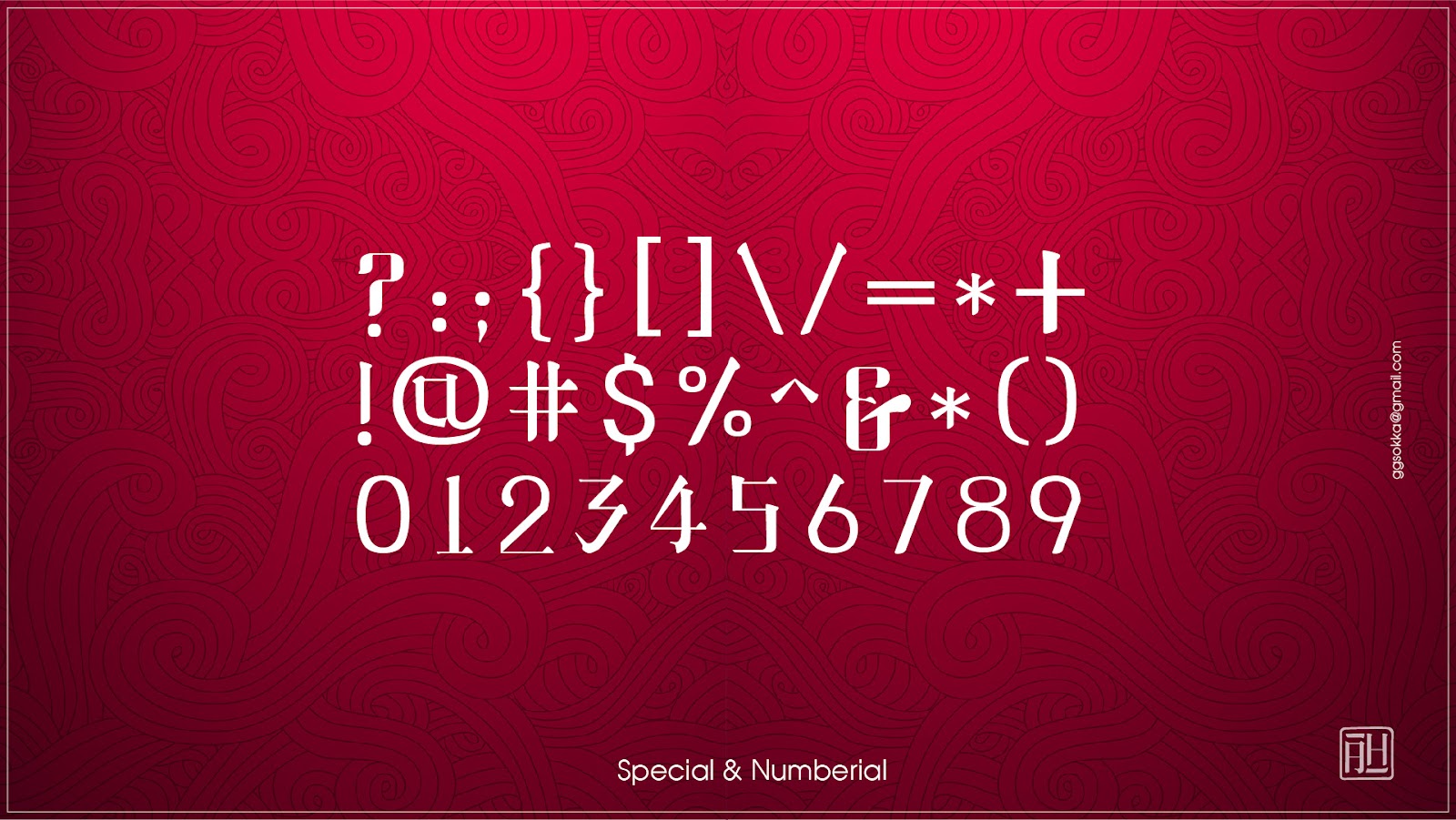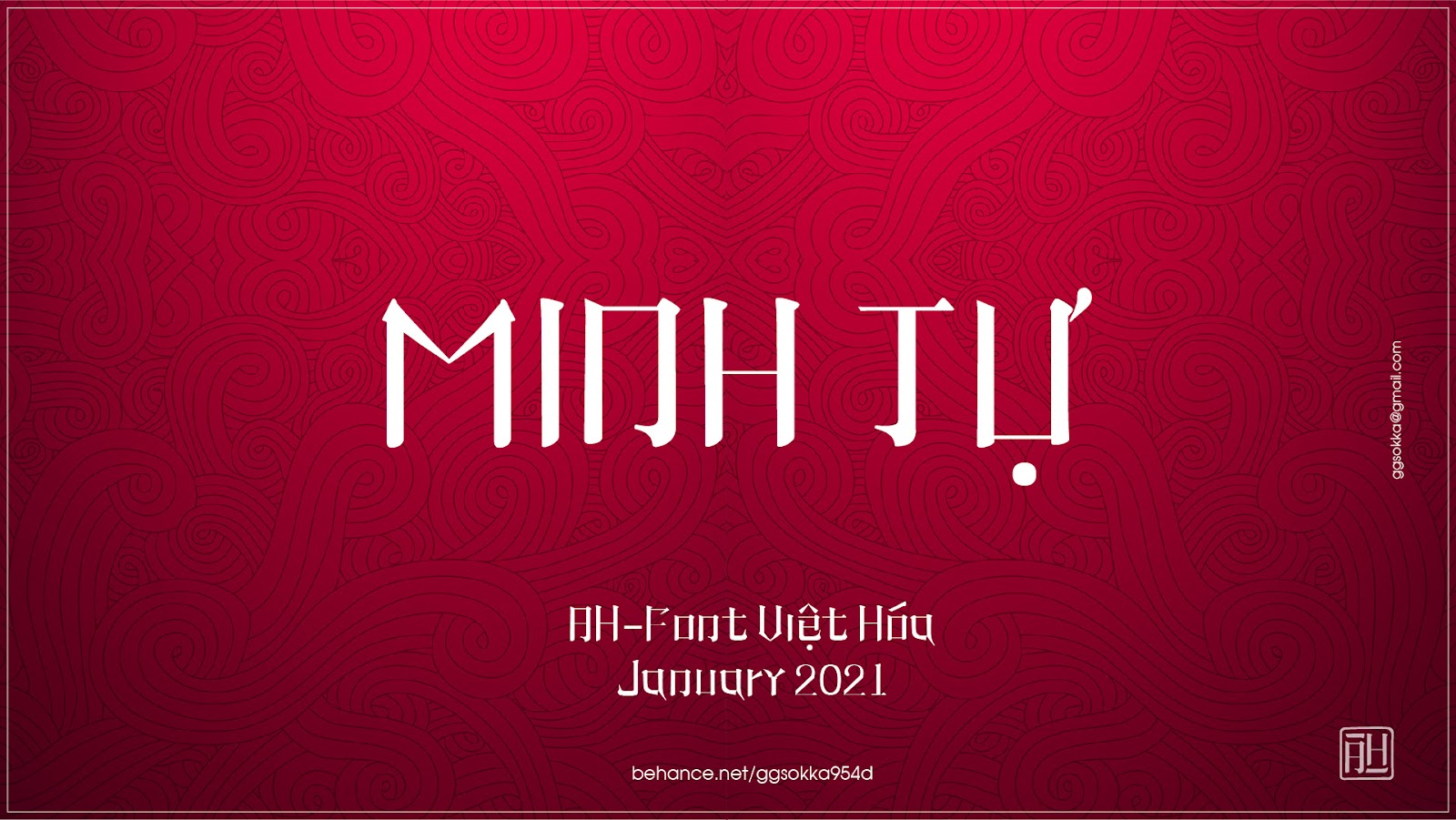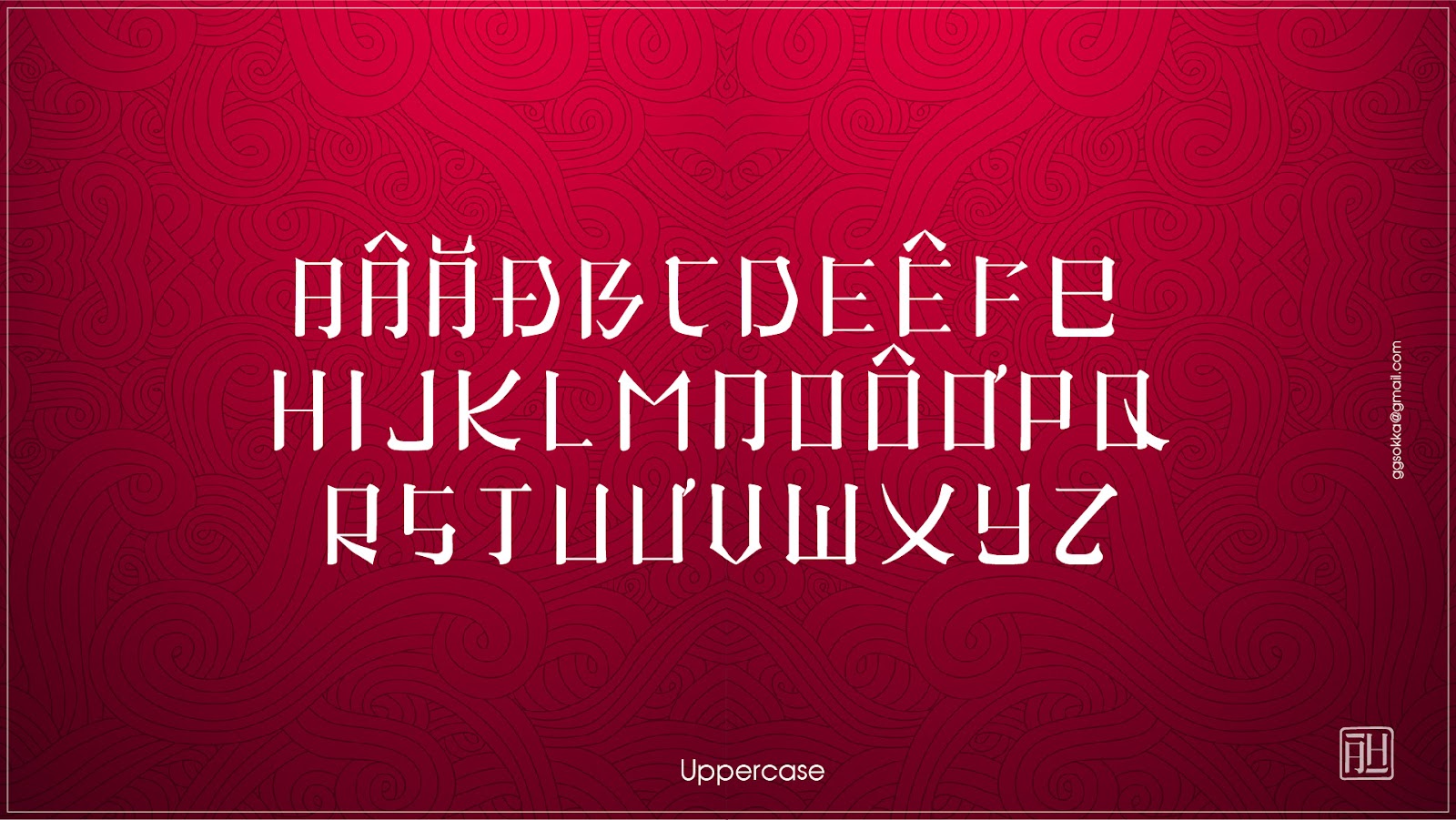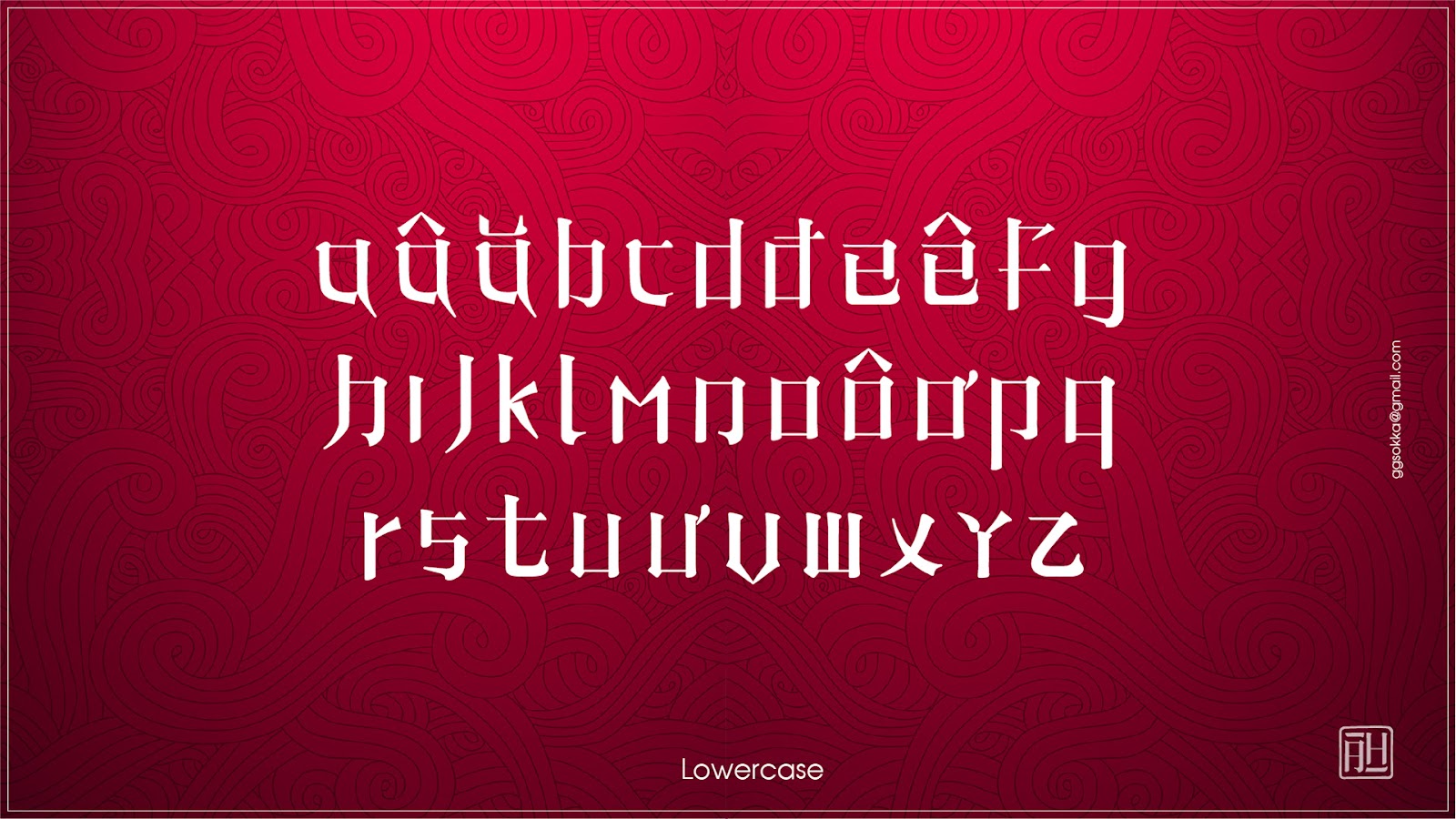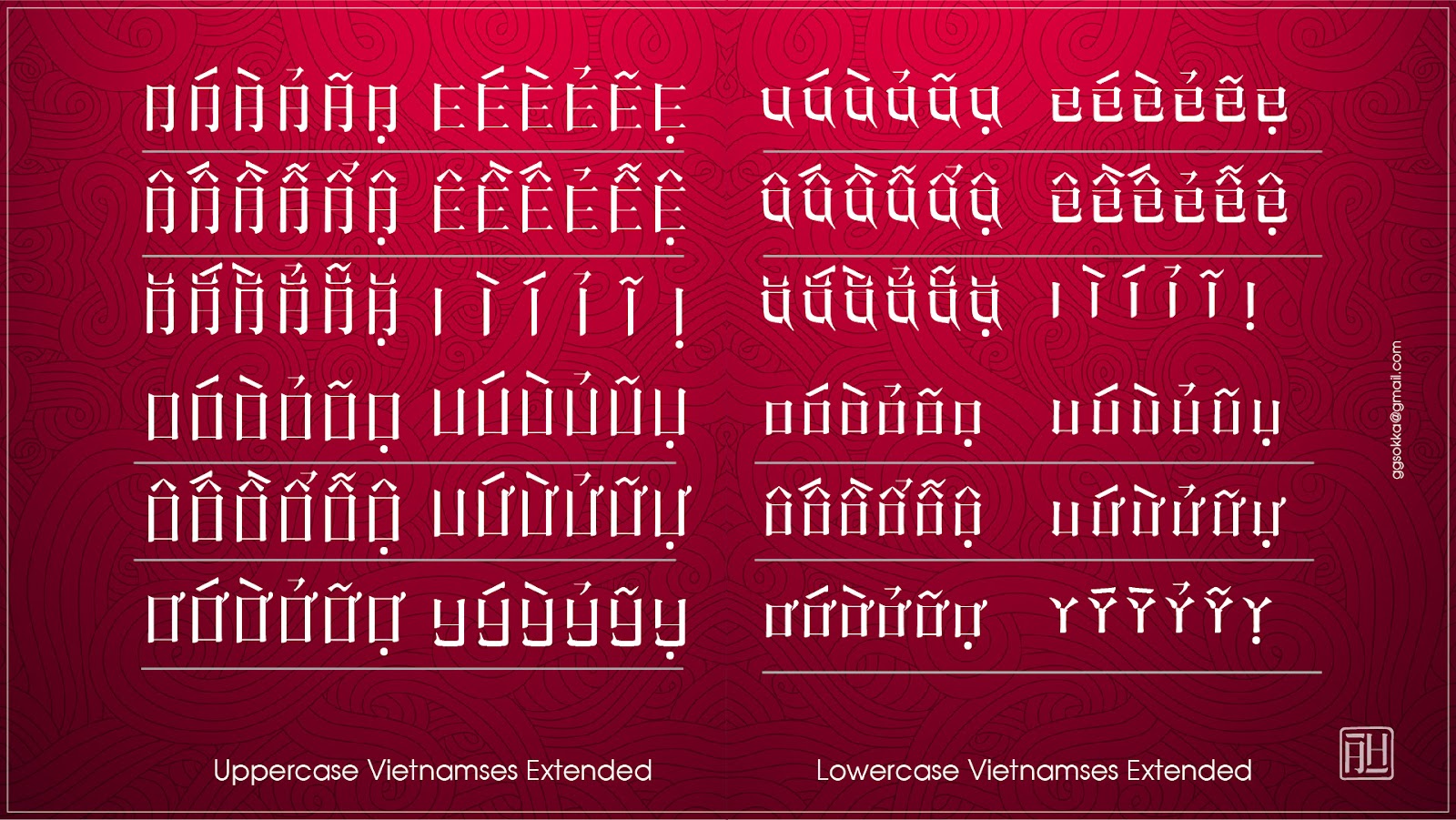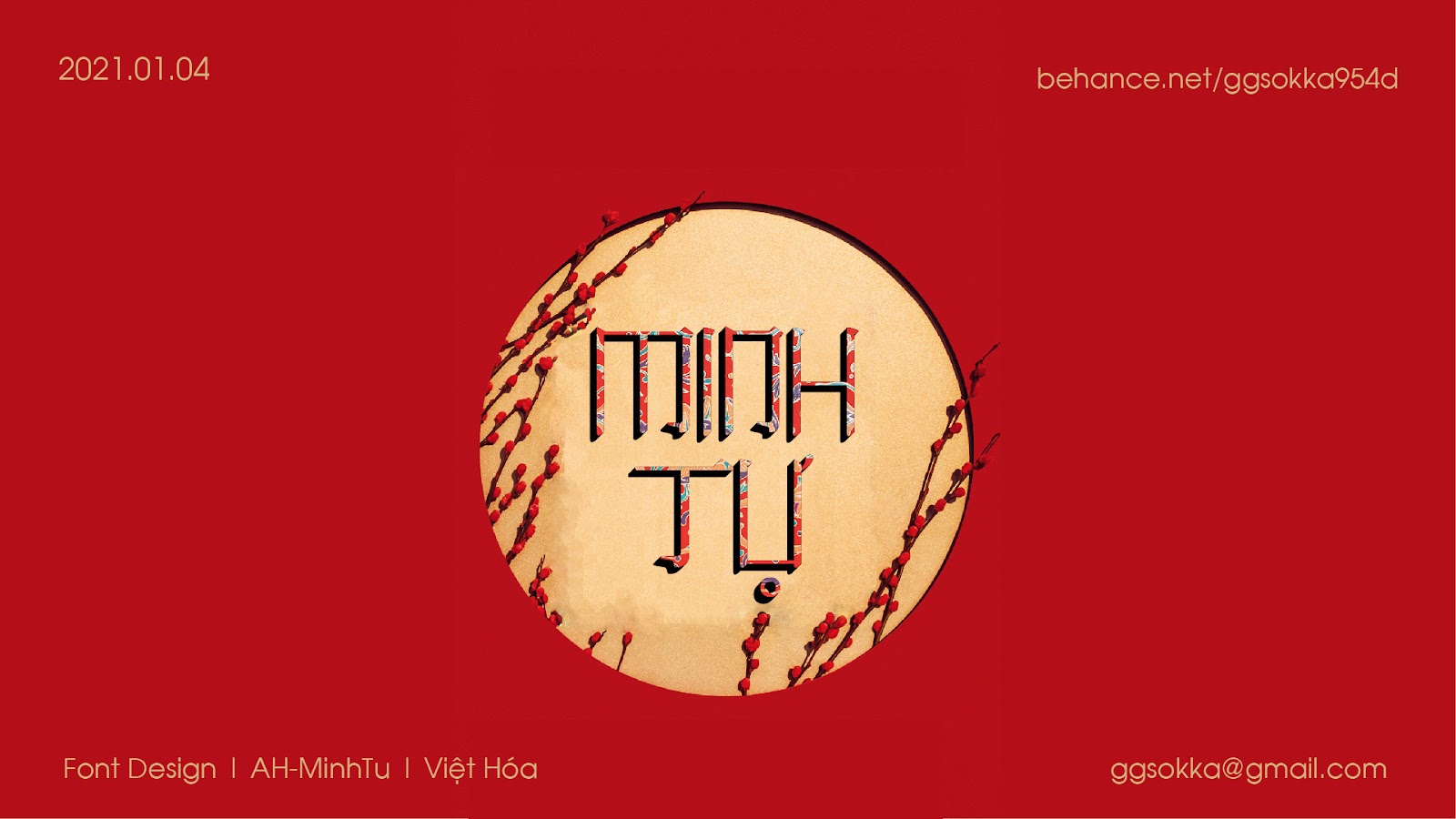
Font chữ Minh Tự Việt Hóa cực đẹp
Font Minh Tự được thiết kế bởi GG SOKKA một font thư pháp khá ấn tượng với các nét chữ lấy cảm hứng từ các font chữ Trung Hoa. Font chữ khá phù hợp cho các thiết kế dịp năm mới, trung thu hoặc cổ trang.